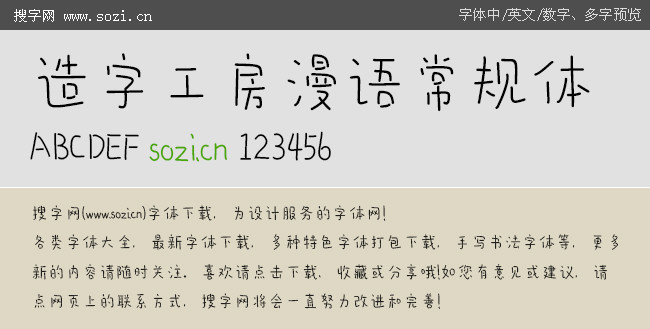
造字工房漫語常規(guī)體
搜字網(wǎng)提供一款造字工房漫語常規(guī)體中文藝術(shù)字體下載,造字工房漫語常規(guī)體結(jié)構(gòu)自然灑脫,字形活潑、可愛,造型生動(dòng)有趣,具有靈活的適用性。此款字體適用于兒童讀物、報(bào)刊雜志標(biāo)題、廣告設(shè)計(jì)等領(lǐng)域。